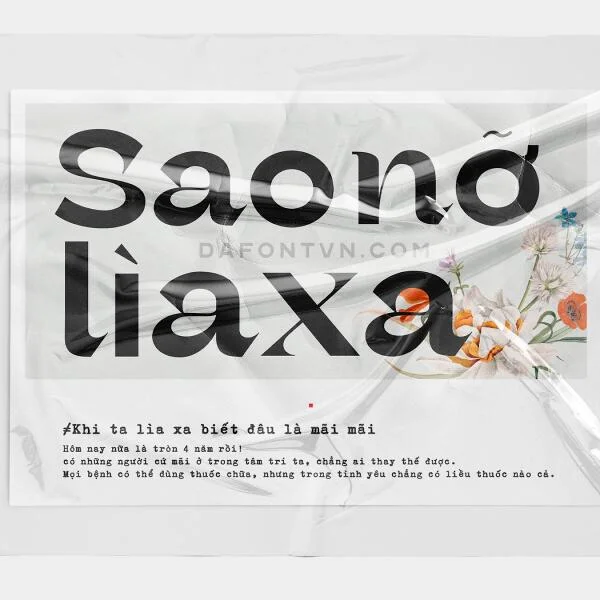
Download Font Despair Việt Hóa - 1 phông chữ phá cách, táo bạo
Font Despair là một sự kỳ cục vô tình táo bạo với chữ thường hẹp, chữ hoa rộng và dấu chấm câu lạ. Chỉ chứa các ký tự Latinh và Cyrillic cơ bản. Tải về ở cuối bài viết !
Tổng quan về Font Despair
DespaiR (rev) là một phông chữ gothic với các nét chữ được thiết kế theo dạng vẽ tay trên giấy vì vậy khá phù hợp cho các thiết kế bìa truyện, typo, banner...
Font Despair việt hóa đầy đủ, được tối ưu, chỉnh sửa và thay đổi một chút so với font gốc, dấu được sửa lại cho phù hợp với dấu tiếng Việt.